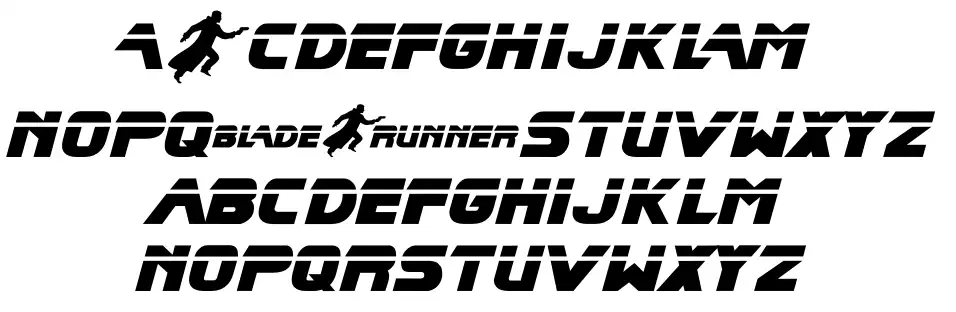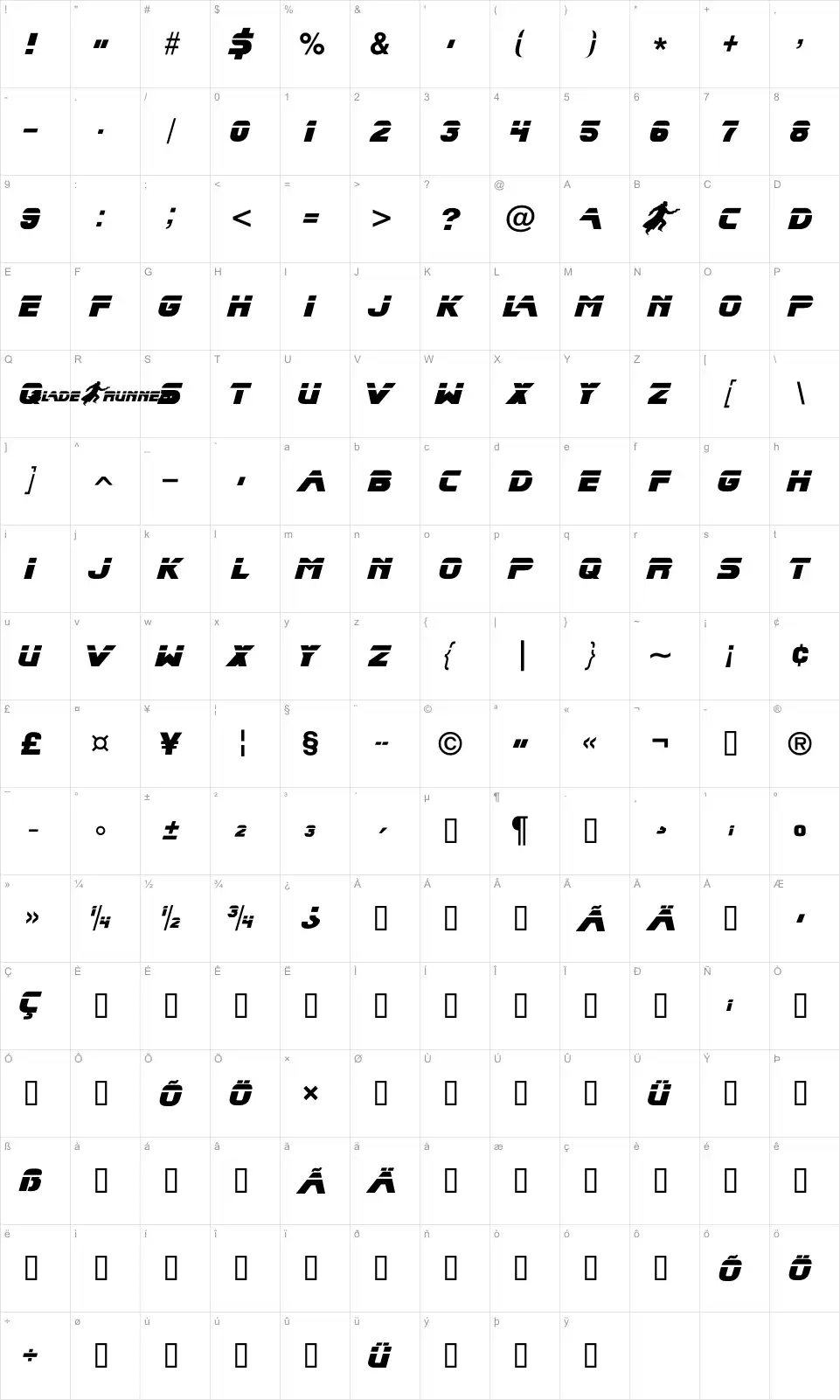
Descubra a Blade Runner Movie Font, projetada por Phil Steinschneider, uma fonte que transmite a atmosfera futurista e tecnológica tão característica da aclamada trilogia de filmes Blade Runner. Esta fonte pertence à categoria de Tecnologia e ficção científica, um elo direto com o imaginário cyberpunk do cinema. Se você busca uma fonte que dê um toque criativo a qualquer projeto de design, essa pode ser a escolha perfeita. Com uma licença gratuita, tamanho de arquivo compacto (44 KB) e disponível em formato TTF, é fácil de usar e integrar em seu projeto. Se você está procurando por uma fonte que combine o poder da tecnologia com a estética futurista da ficção científica, Blade Runner Movie Font é uma excelente opção. Para se familiarizar com sua aparência e garantir que ela se adapte perfeitamente ao seu trabalho, você pode fazer download ou gerar uma prévia de texto personalizada online para ver como ela se assemelha a Blade Runner. Como a Blade Runner Movie Font é uma fonte de tecnologia, projetada para a categoria de ficção científica, você pode encontrá-la em seu site oficial através deste link: http://www.pressroom.com/~philips.